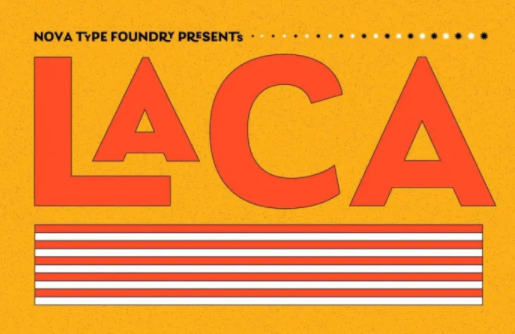
[Creativemarket] Laca Font (2021)
Laca - это полусантиметровый шрифт, вдохновленный ретро-португальской упаковкой мыла.
Laca - это португальское слово, означающее "лак для волос". Исходной точкой было создание шрифта, который вызывал бы знакомое ощущение близости и тепла, но при этом имел бы современный вид, чтобы он хорошо работал на современных платформах. Это живой шрифт, который привносит в текст текстуру и индивидуальность. Идеально подходит для брендинга и любых коммуникаций. В стилистическом наборе есть версия с вертикальным курсивом, которая придает шрифту еще больше дружелюбия. В результате получился универсальный шрифт, обладающий множеством функций OpenType, что дает дизайнеру возможность выбора стилистических вариантов.